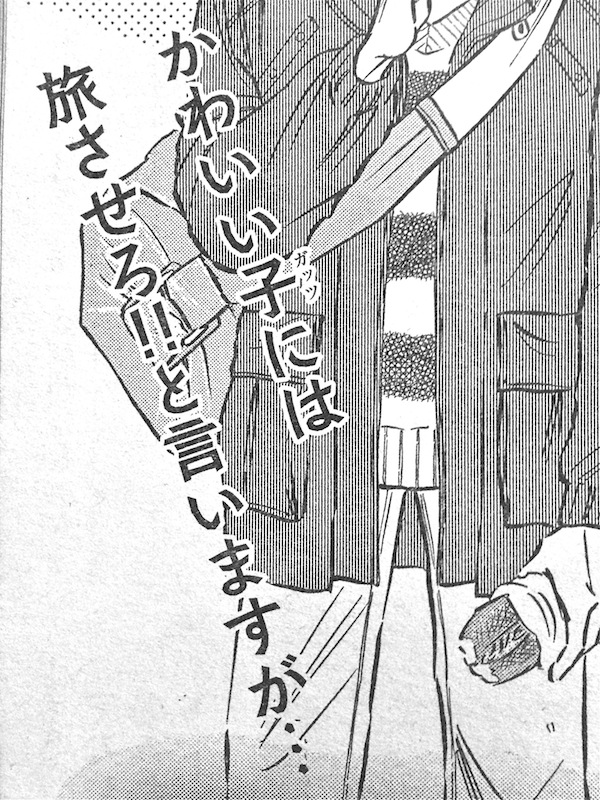
本の表紙  さとうゆたか  2015年12月17日(木) 11:22
書名:アナとエルサ 自分を好きになる10のレッスン
著者:PHP研究所
発行:PHP研究所
ゲーム ローグ・レガシーの動画  あられ  2015年12月14日(月) 10:01  HP
動画で使われてます。私が買ってないので確認できないのですが、ゲーム内の文字もあられなんじゃないかなと言う気がします。
ファミマのおつまみ  takumi  2015年12月3日(木) 18:40  HP
学校の近くのファミリーマートの中で見つけたあられ書体です。
古めかしい雰囲気がよくおつまみのイメージと合っていますね。
あられ書体で「おつまみ」が少しでも美味しそうに感じられるなら、作者としてうれしいですね…。
連載漫画の扉ページ  さとうゆたか  2015年9月25日(金) 11:39
ビッグコミック増刊号に連載されている業田良家の「機械仕掛けの愛」第30回。
キャンペーンロゴ  さとうゆたか  2015年9月13日(日) 11:08
北海道の知床で、あちこちに貼られている「ヒグマえさやり禁止」のステッカー。
緑のはなしをしましょう。  さとうゆたか  2015年5月28日(木) 15:31
春の都市緑化推進運動のポスター。
絵本「しっぽがぴん」  Maki  2015年3月5日(木) 23:45
画像が無くてごめんなさい。おくはら ゆめさんの絵本「しっぽがぴん」であられ書体が使われています。表紙は作者名のみですが本文にも使用されています。
←本文の一部です。
記事タイトル  さとうゆたか  2015年2月21日(土) 10:21
新聞に折り込まれていた地域の情報PR誌。
映画『BIG EYES』  Maki  2015年2月4日(水) 10:40
ポスターや公式サイトの和文書体として使われているのを発見しましたよ。